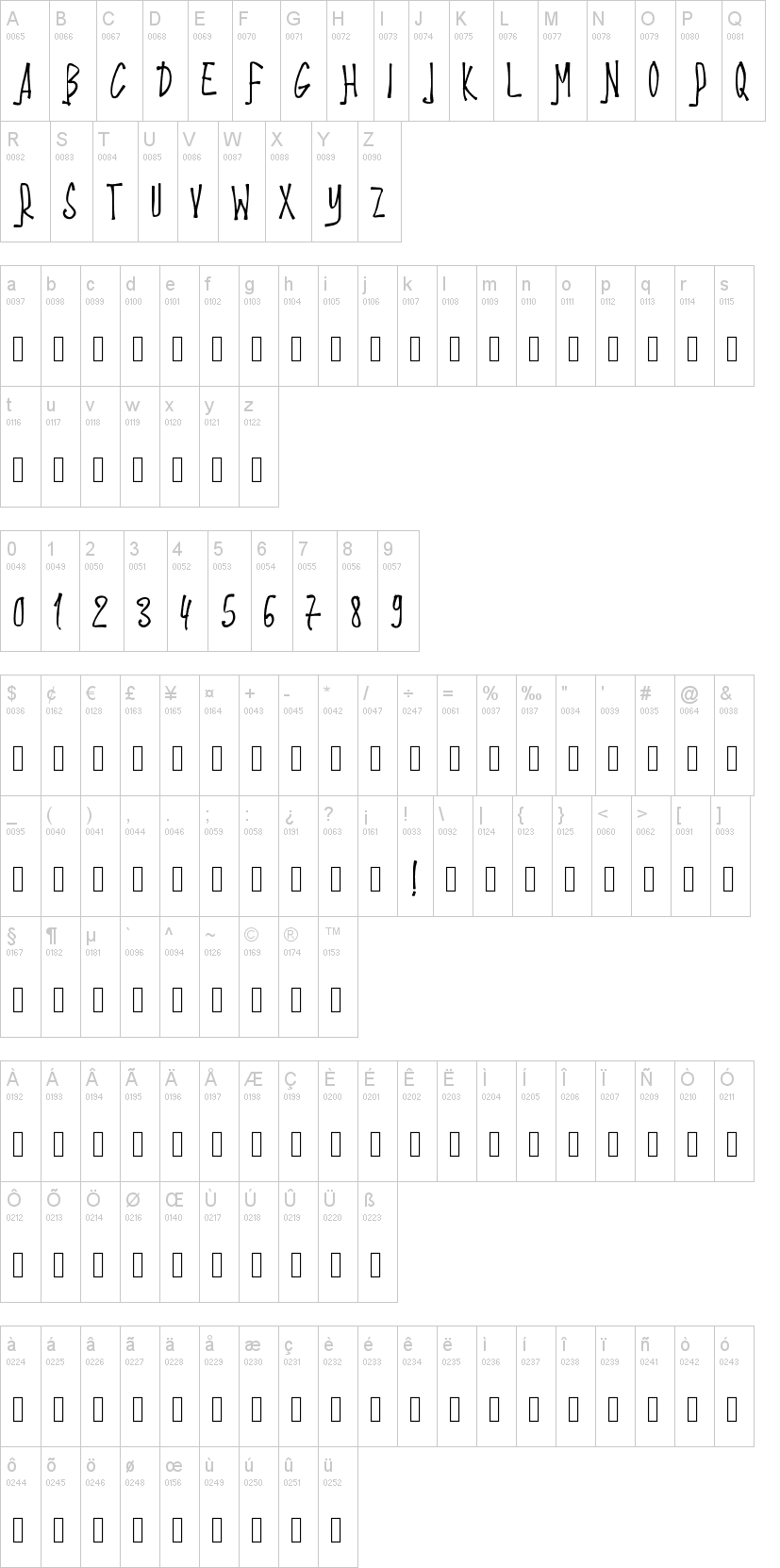
PW Stixs是一种免费的手写字体,其设计灵感来自于手写胶带标签。它具有现代且简洁的外观,由白色背景和黑色字体组成,因此非常适合在深色背景上使用。该字体包含大写字母、小写字母、数字和常用符号,非常适合用于设计卡片、海报、广告和其他文本项目。此外,PW Stixs字体还带有一些额外的特殊字符,例如心形和星形,使得这种字体非常适合用于创意项目和个性化设计。内容介绍
PW Stixs是一款非常不错的手写艺术字体,具有很好的视觉感,适合于文化类的宣传设计、商业类品牌的广告和产品包装设计以及个性化文字排版等较多场景。